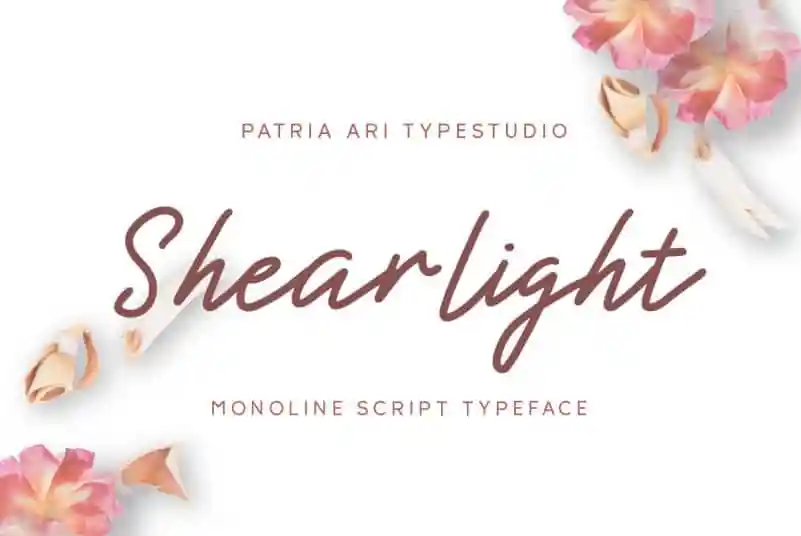
Shearlight Script Font – Download Grátis
A Shearlight Script Font é uma bela tipografia script monoline com formas elegantes mas também fortes. Seu design fluido e arredondado traz autenticidade a qualquer projeto de texto, enquanto sua simplicidade oferece um toque moderno sem perder o charme do script. Ideal para gráficos de marketing digital ou desenhos criativos que buscam uma harmonia entre elegância e simplicidade, esta fonte é perfeita para quem busca expressar seu trabalho com graça. Composta em apenas linhas, a Shearlight Script Font proporciona um toque único que transforma qualquer design de forma elegante e sofisticada.